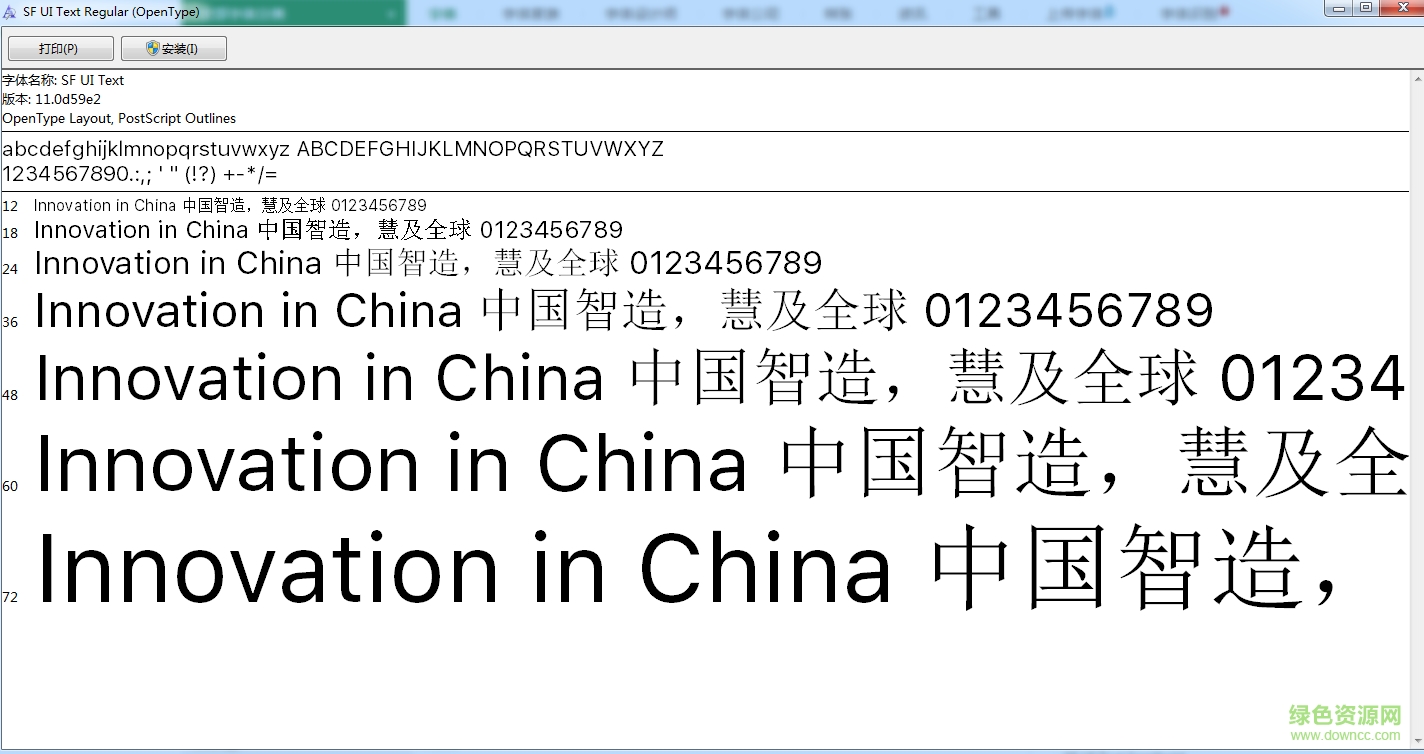
sf ui text regular字體是一款漂亮得體的英文無襯線字體,字體筆畫干凈,結(jié)構(gòu)規(guī)范,可用作ui設(shè)計(jì)、廣告設(shè)計(jì)、平面設(shè)計(jì)等領(lǐng)域,有需要者快來綠色資源網(wǎng)下載吧!
文本模式(SF UI Text)和展示模式(SF UI Display)。 文本模式適用于小于20 points的尺寸,展示模式則適用于大于20 points的尺寸。當(dāng)你在你的app中使用San Francisco時(shí),iOS會(huì)自動(dòng)在適當(dāng)?shù)臅r(shí)機(jī)在文本模式和展示模式中切換。